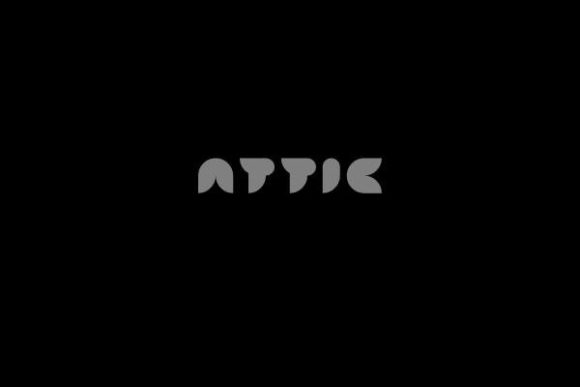
Fuente Attic para titulares, carteles y proyectos de marca
Attic es una fuente de exhibición moderna y llamativa que impacta cualquier diseño. Perfecta para pósteres, folletos e impresiones, esta fuente ofrece infinitas posibilidades para proyectos creativos.
- Tipografía de visualización en negrita
- Ideal para carteles y folletos.
- Infinitas posibilidades de diseño